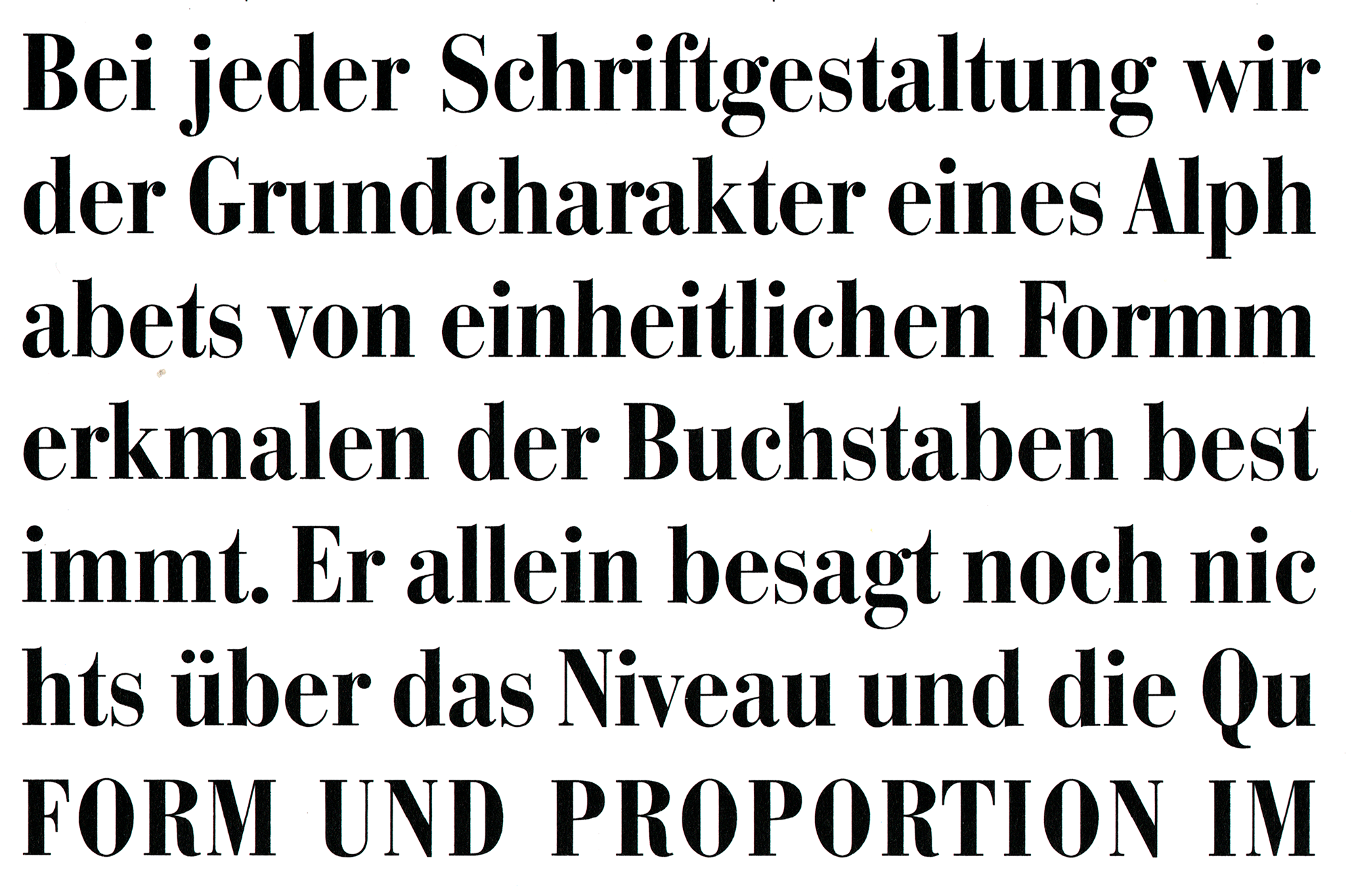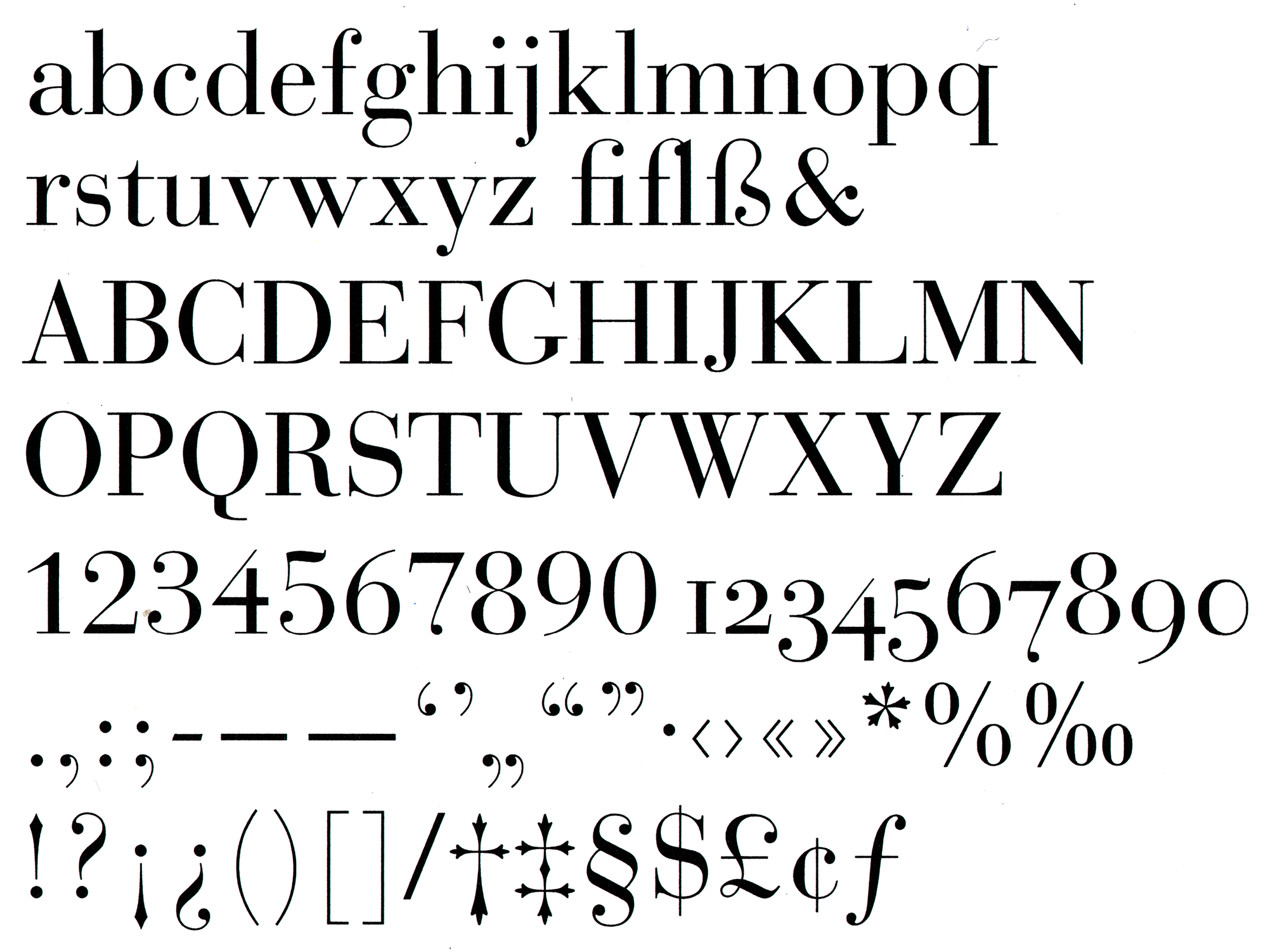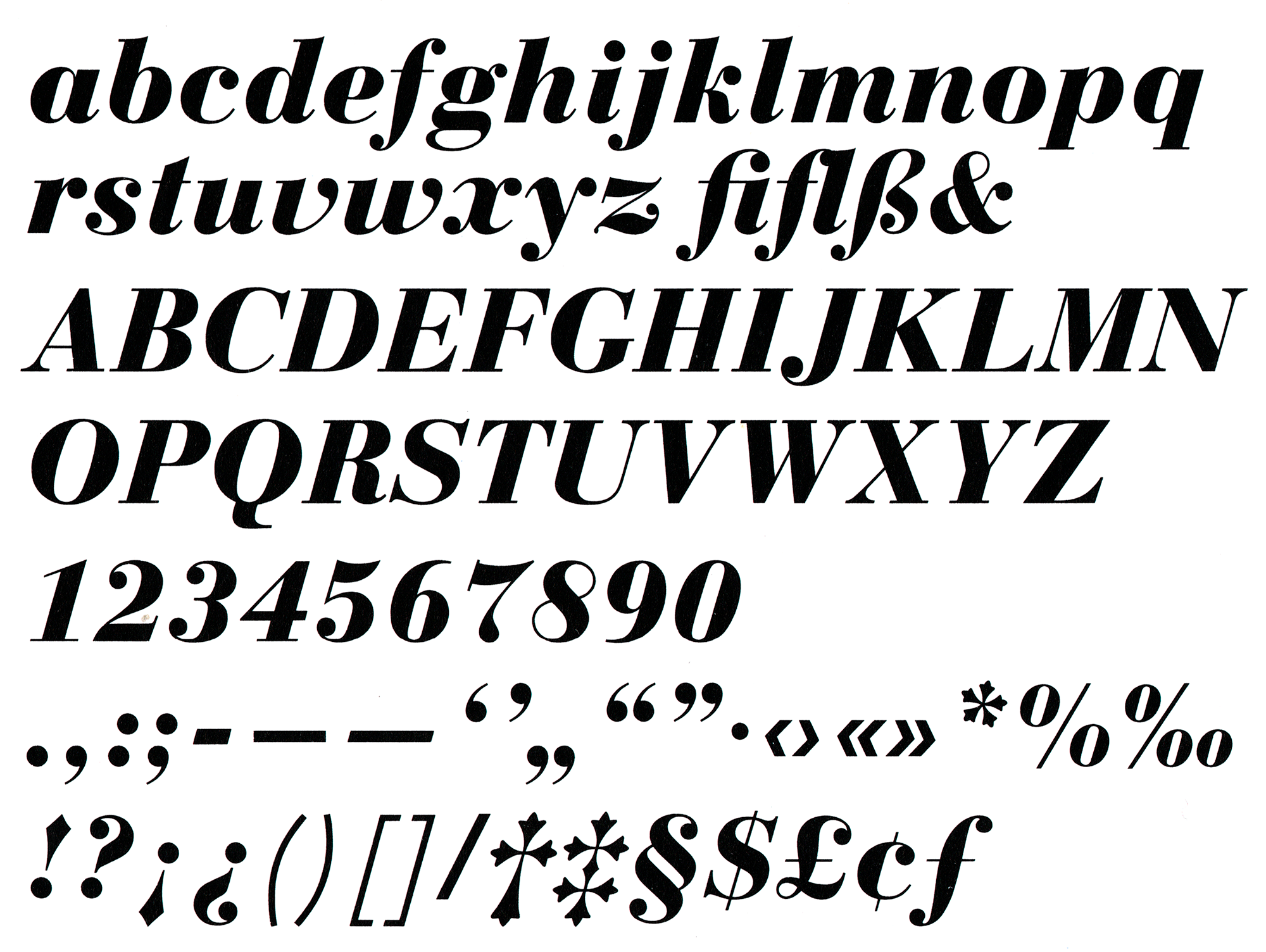
- 1926
- Antiqua statisch
Die Bauer Bodoni ist ein bekannter und erfolgreicher Neuschnitt der klassizistischen Schriften von Giambattista Bodoni. Die Familie erschien ab 1926 bei der Bauerschen Gießerei in Frankfurt/M. und wurde in der Folge weiter ausgebaut. Bis in die 1950er-Jahre bestand die Schrift aus drei Strichstärken (normal, halbfett, fett) mit zugehörigen Kursiven. Im Fotosatz waren auch zwei schmale Schnitte erhältlich.
Alle acht genannten Schnitte sind heute über Linotype mit Kapitälchen und erweiterter lateinischer Belegung verfügbar.